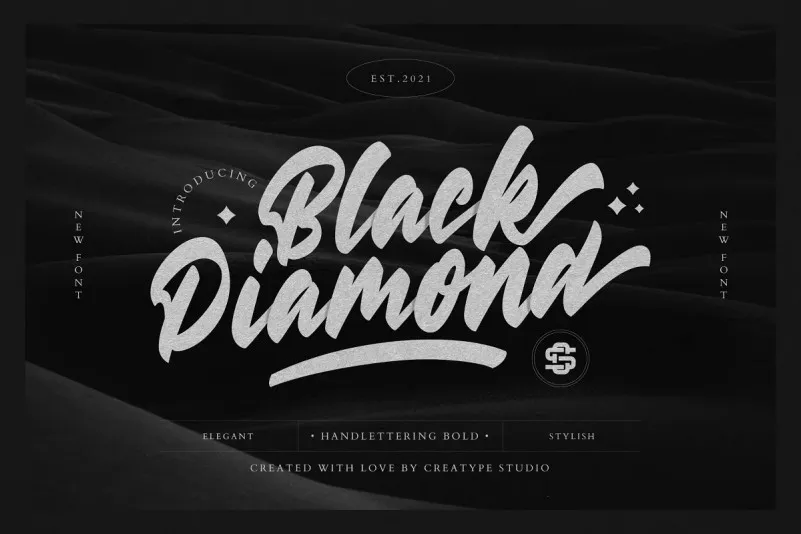
A fonte “Black Diamond” é uma escolha ideal para quem busca elegância contemporânea na tipografia. Criada à mão com um pincel único, esta fonte tem um ar bold e moderno que se destaca por sua elegância clássica e sofisticação estilizada. Através do seu formato casual e fluido, o texto ganha um toque refinado e vibrante, perfeito para ambientes de design gráfico com forte característica visual. Idealmente aplicada em materiais digitais ou impressos, a “Black Diamond” combina perfeitamente com a categoria Script Fonts. O designer 99designs criou uma fonte que se destaca pela sua personalidade única e pelo estilo moderno, combinando elegância clássica com um toque sofisticado. Não há dúvida de que esta é uma escolha excelente para quem busca uma fonte que seja tanto versátil quanto irresistivelmente bonita.